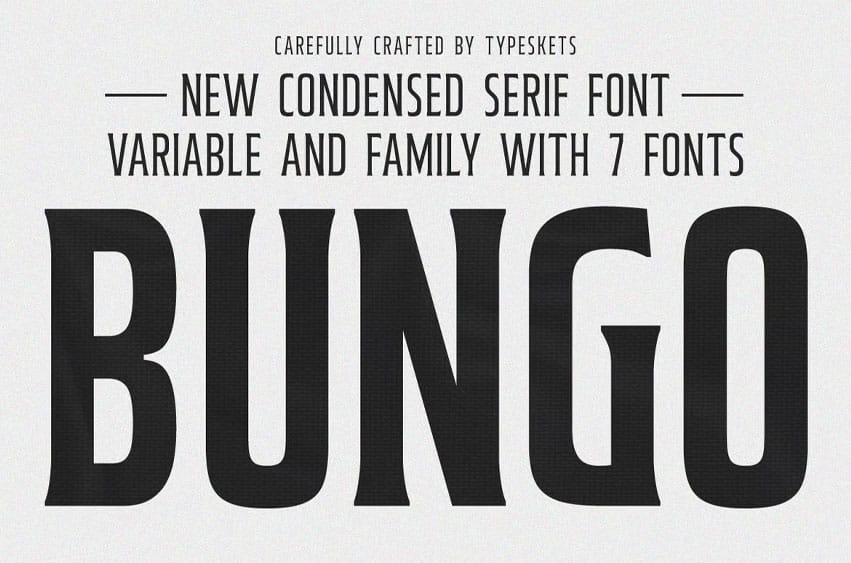
Bungo Font adalah condensed serif font yang tebal, modern, dan berkarakter kuat. Dibuat untuk memberikan kesan powerful, authoritative, dan high-impact, BUNGO sangat cocok untuk judul besar, poster, editorial, branding, sport typography, dan desain modern lainnya.
Font ini hadir sebagai variable font dengan 7 gaya berbeda, memungkinkan fleksibilitas penuh bagi desainer dalam menciptakan hierarki visual dan gaya yang konsisten. Bentuk serif yang memanjang dan proporsi yang rapat membuatnya ideal untuk tampilan yang dramatis namun tetap elegan.